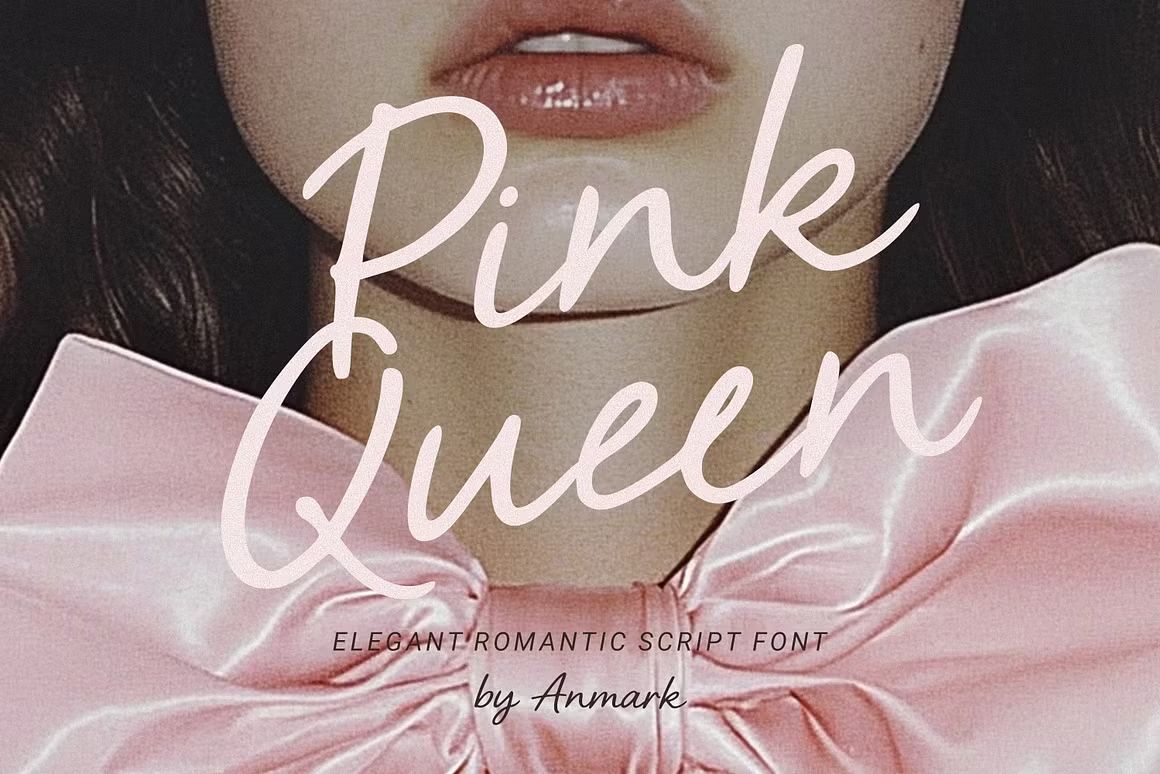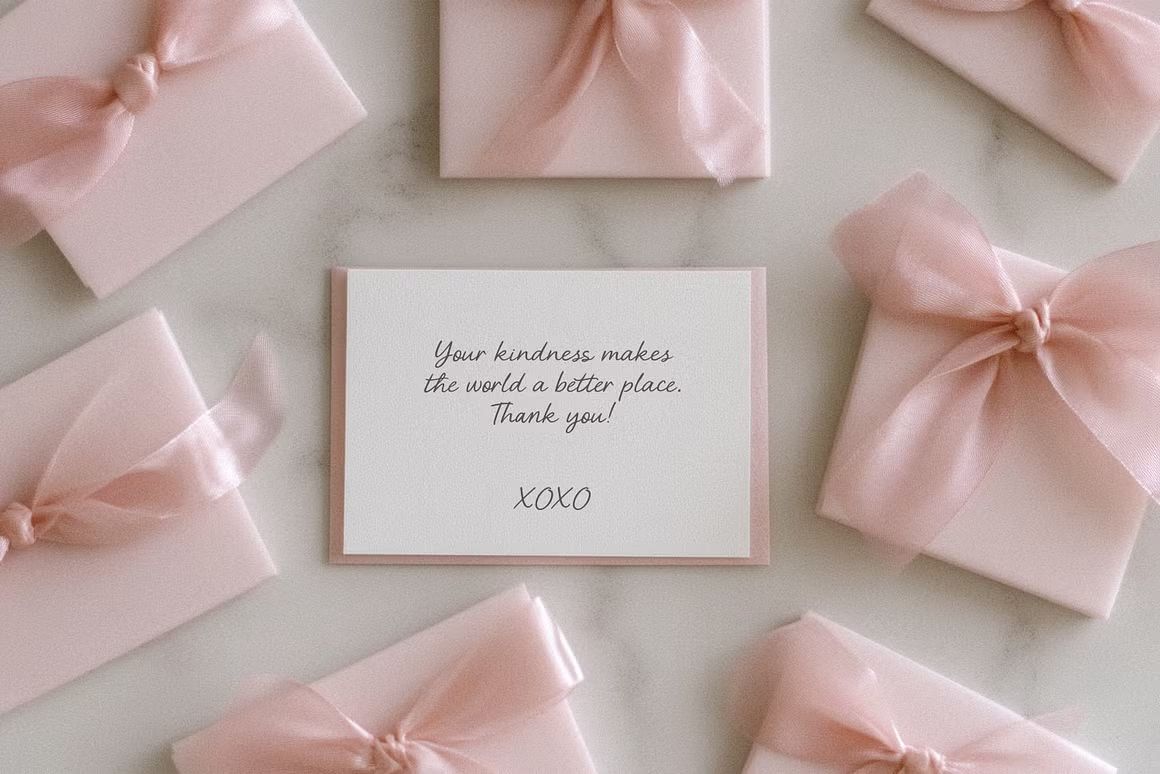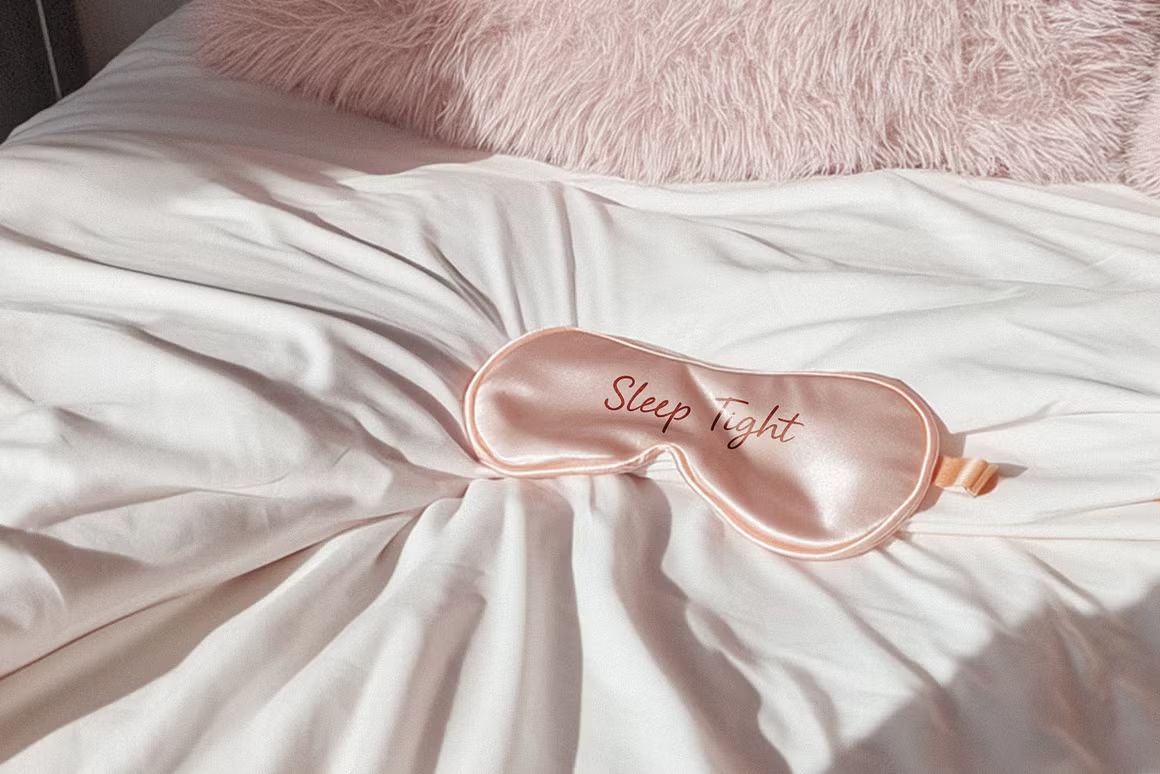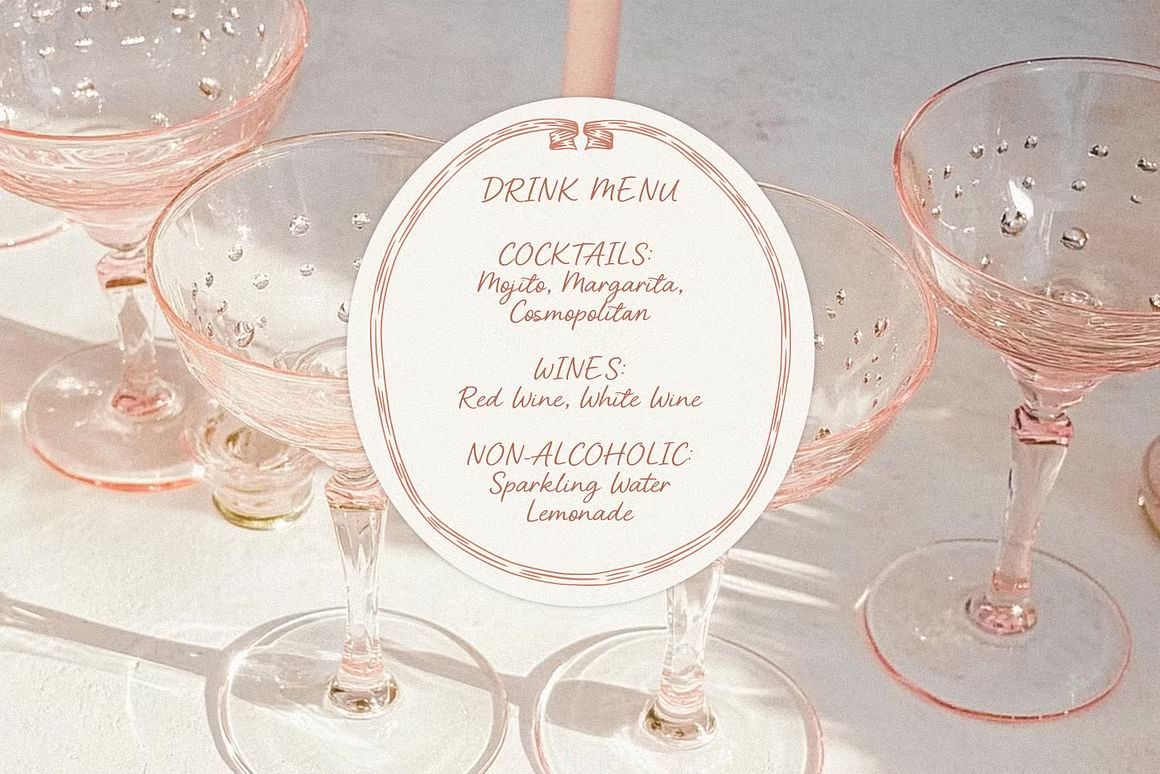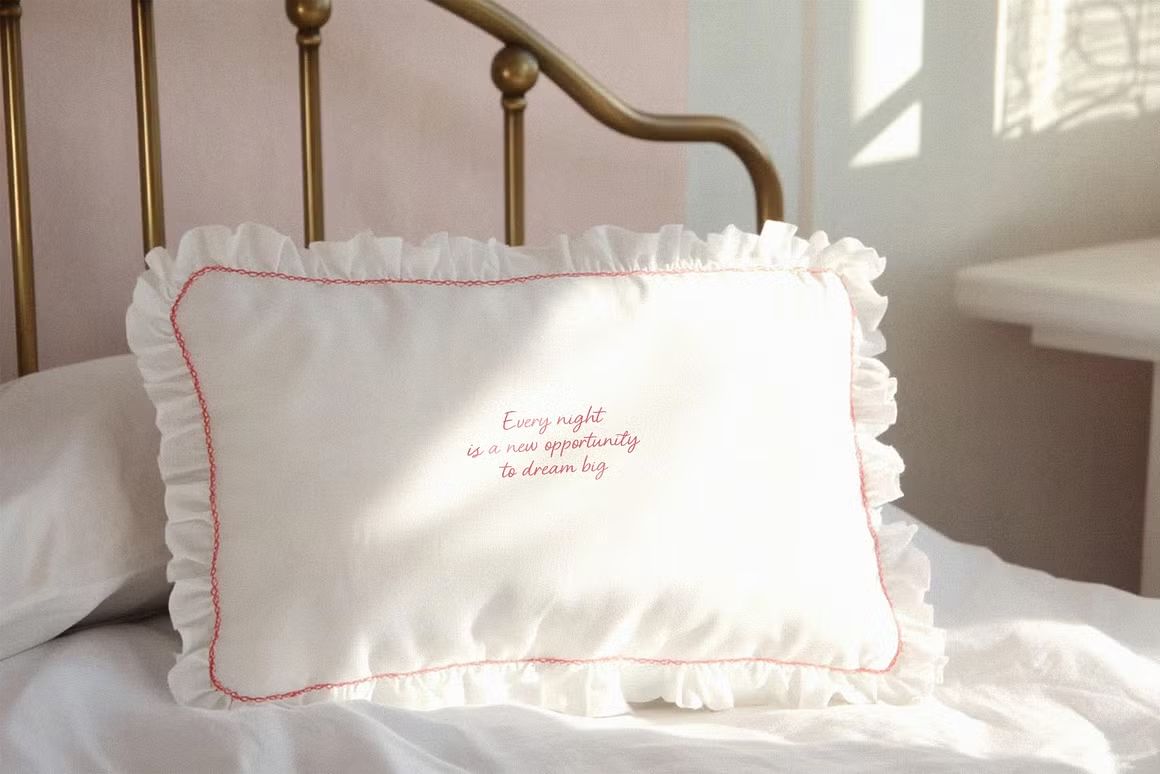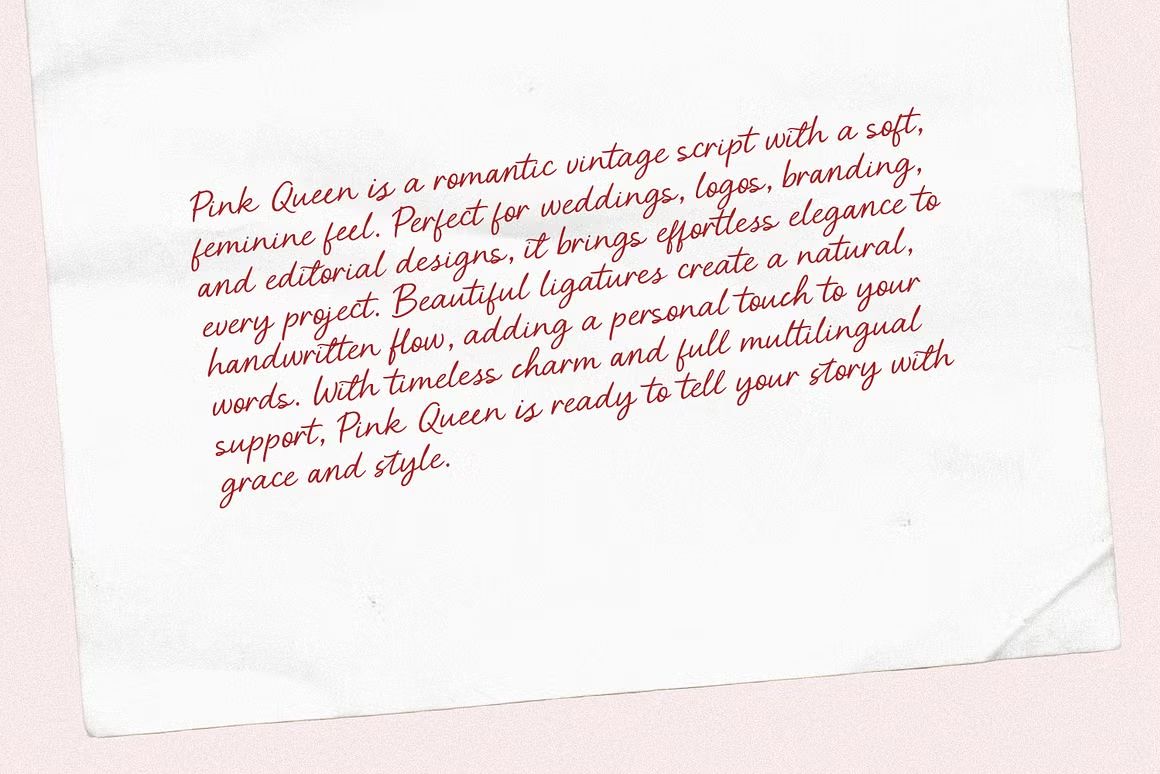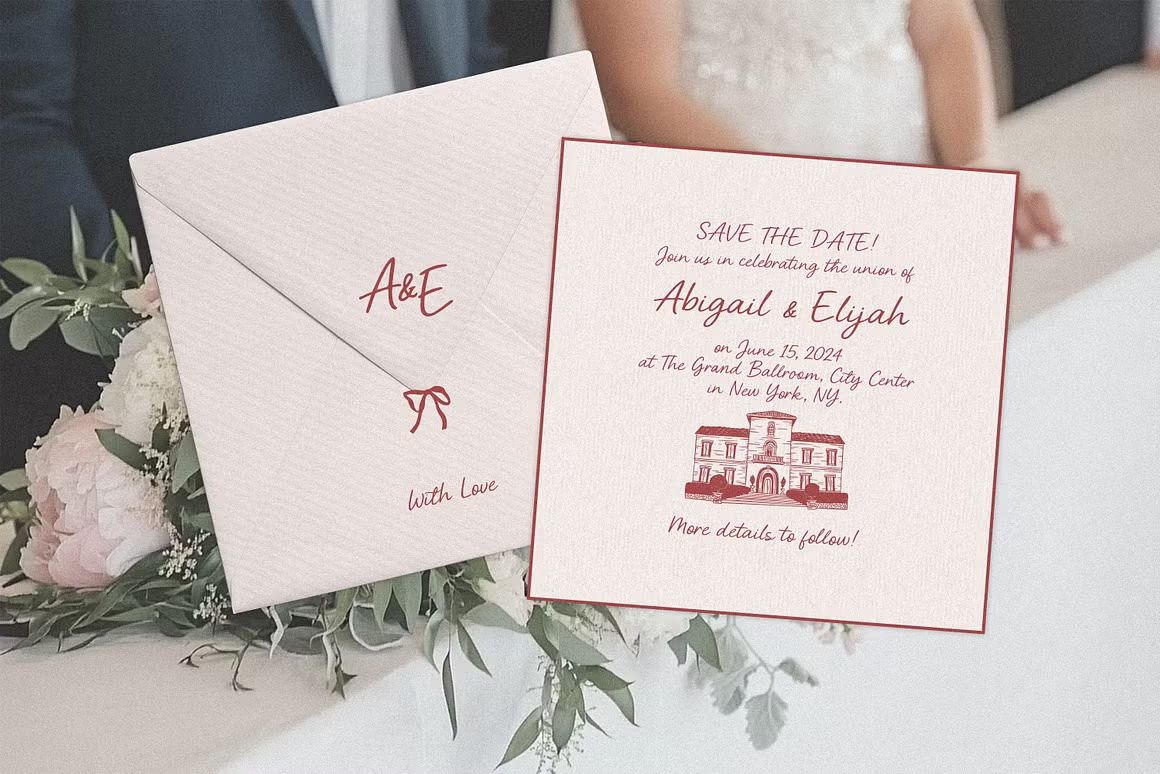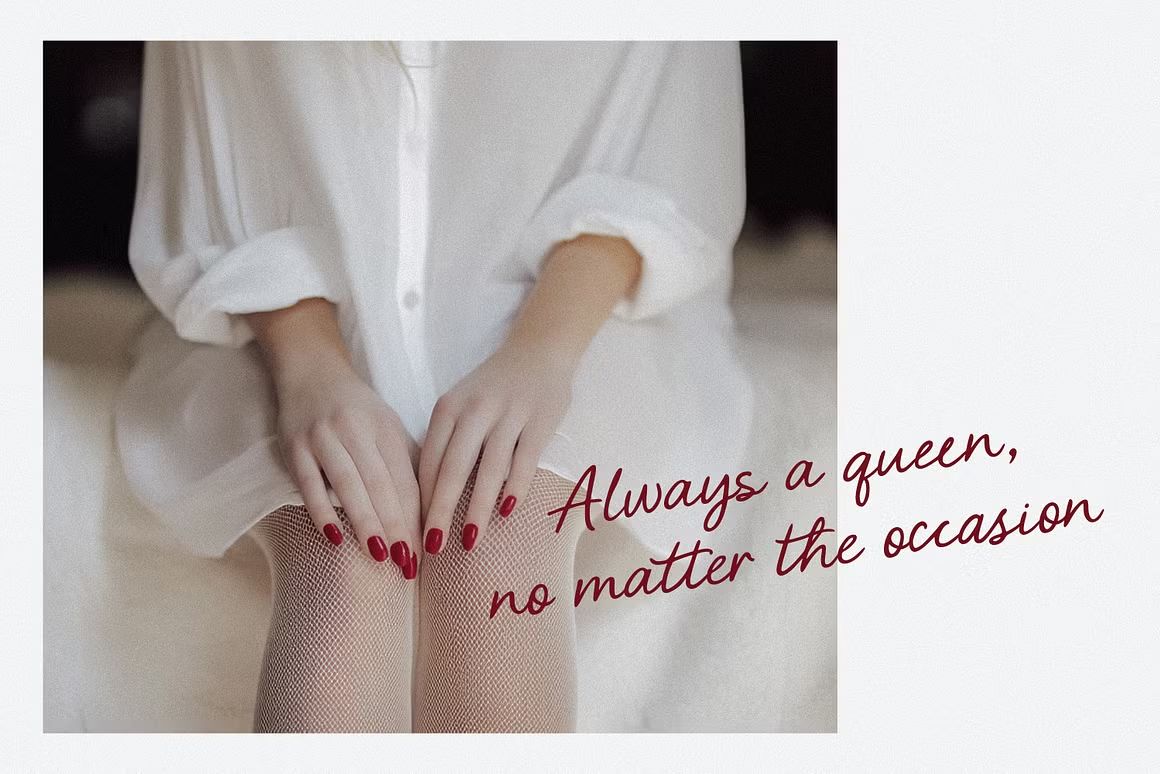
Pink Queen – Script Font
Font script elegan dan feminin dengan gaya tulisan tangan modern, cocok untuk desain romantis dan branding stylish.
Pink Queen – Script Font adalah font bergaya tulisan tangan dengan sentuhan feminin, elegan, dan playful. Dengan lekukan halus dan gaya kaligrafi modern, font ini cocok digunakan untuk undangan pernikahan, branding kosmetik, logo fashion, desain sosial media, dan proyek kreatif lainnya. Pink Queen memberikan nuansa anggun dan romantis yang memperkuat karakter visual desain Anda.
• Gaya script modern dengan sentuhan elegan
• Karakter huruf yang halus dan stylish
• Cocok untuk branding, undangan, dan desain feminin